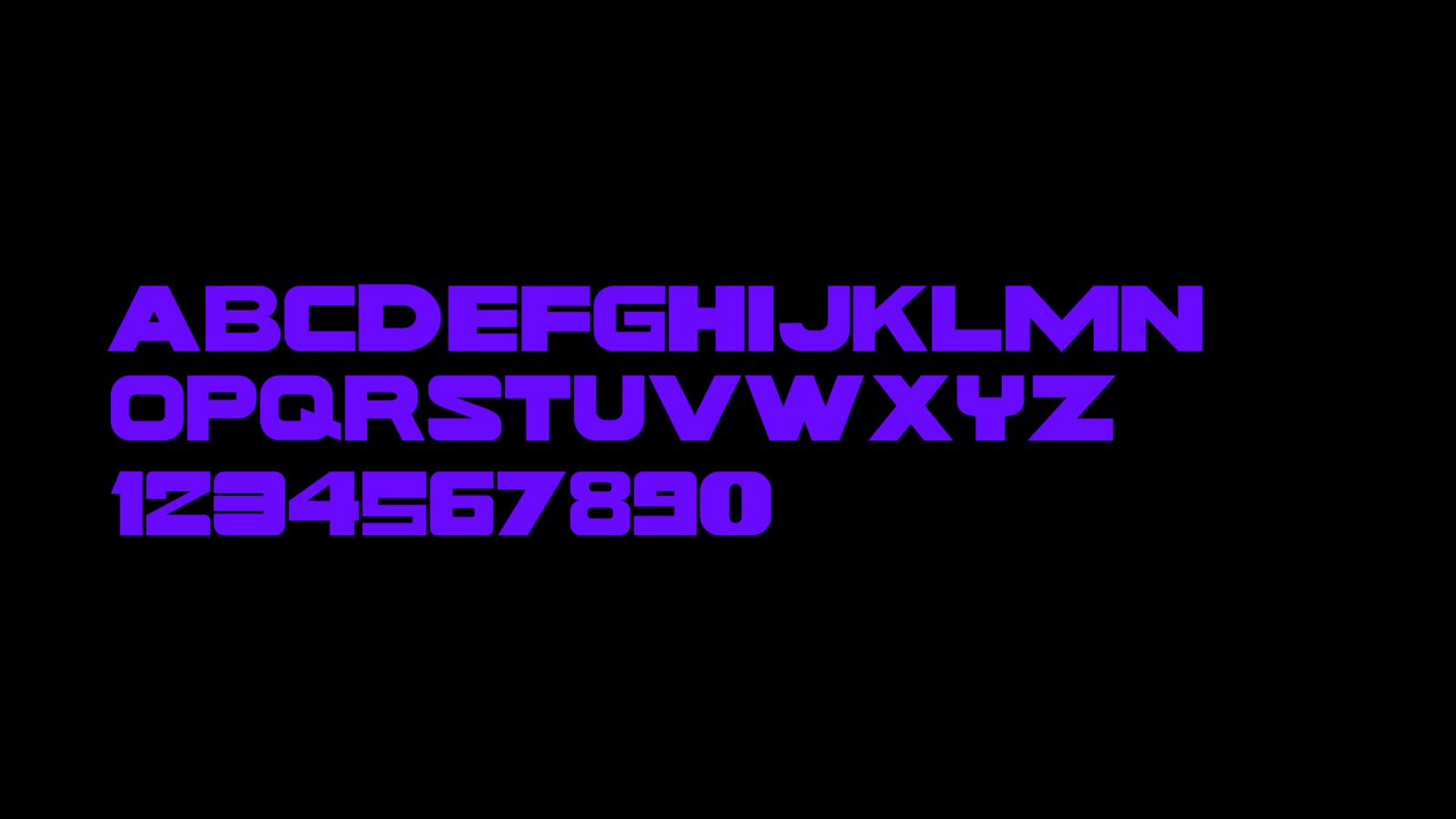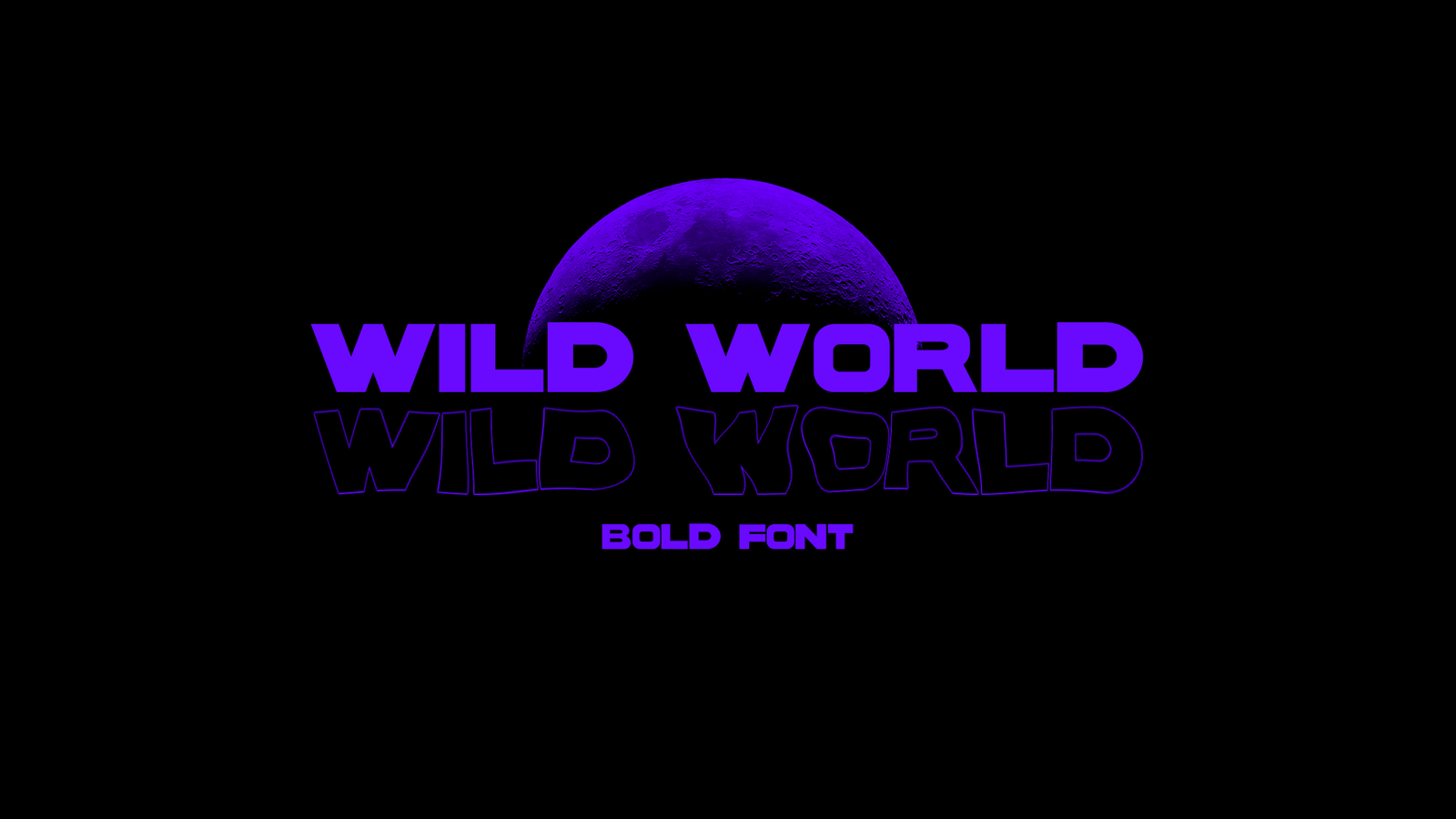
Дополнения Шрифты Татьяна Гапонова 4 апреля 2022 Шрифт - WILD WORLD (Латиница) Стильный шрифт для плакатов и постеров. Формат - OTF. Размер - 200 кб. Автор: Abdullah Mosad Скачать Шрифт - WILD WORLD (Латиница)